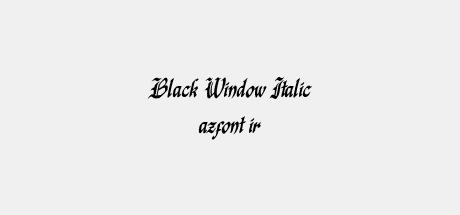
فونت زیبای رایگان Black Window Italic
قلم زیبای Black Window Italic از سری قلم های بسیار زیبا برای تایپوگرافی و لوگو تایپ می باشد.این قلم در وزن Black Window Italic و توسط Billy Argel طراحی و منتشر شده است.